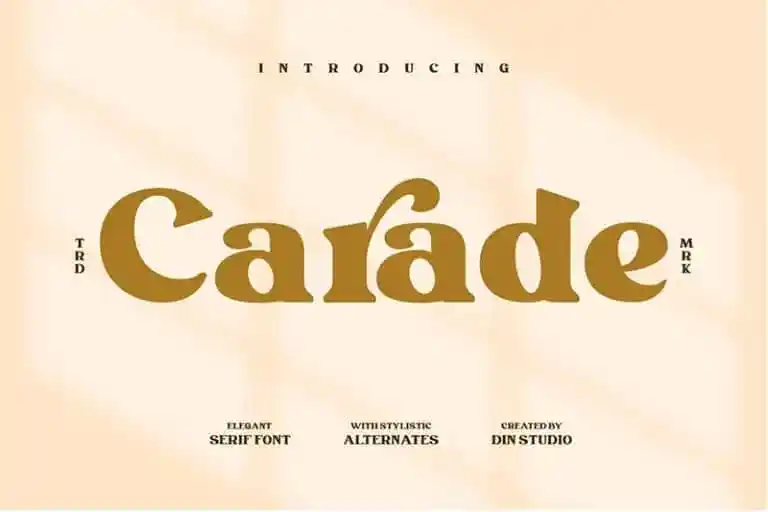
Carade Serif Font
A Carade Serif é uma elegante tipografia moderna concebida para um tipo de projeto que exalta a sofisticação. Ela é perfeita para aplicações que valorizam luxo, estilo fashion e glamour. Com design elaborado para o mundo das artes, o Carade Serif oferece um toque refinado e único em cada letra, tornando-o ideal para projetos de casamento ou qualquer trabalho profissional que precisa de uma identidade visual impecável. Ideal tanto para logomarcas quanto para projetos de branding, a fonte tem a capacidade de se adaptar perfeitamente à criação de mensagens sutis e memoráveis. Seja um quote de destaque, uma marca forte ou elementos visuais que desejam expressar elegância e sofisticação, o Carade Serif está pronto para ajudá-lo a fazer isso. Com base na descrição original em inglês, podemos adicionar detalhes ao nosso texto, mantendo assim a autenticidade da fonte enquanto também criamos um tom informativo e convidativo.